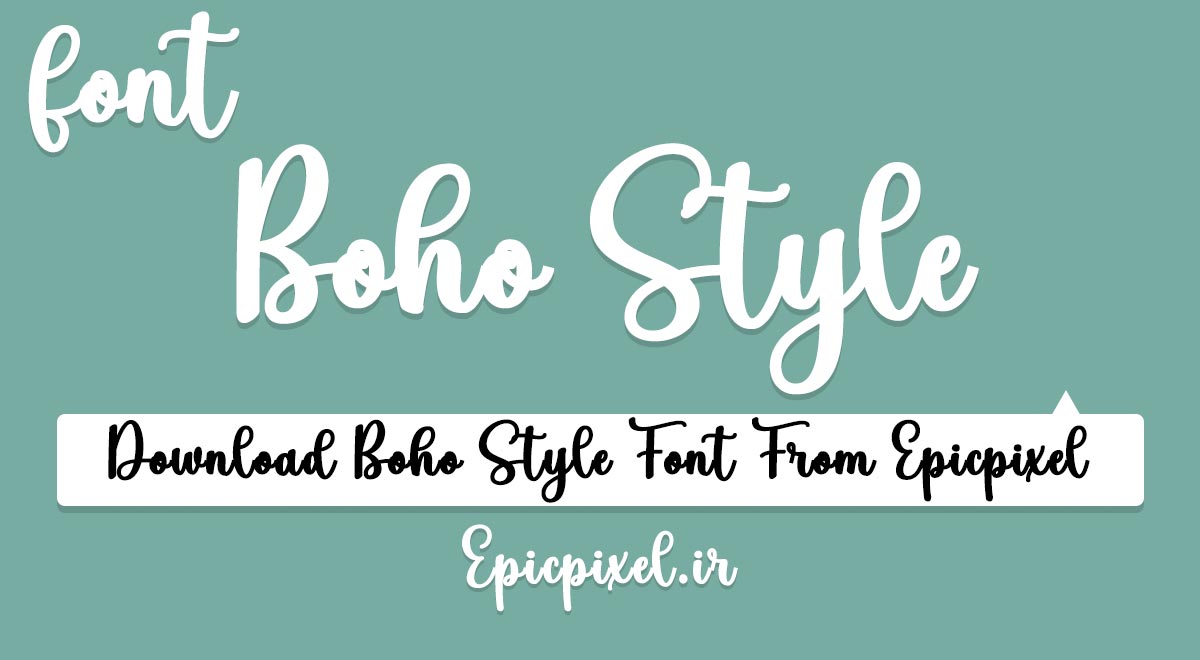
| ⭐ توضیحات | Boho Style Script یک فونت خوشنویسی مدرن از جمله Regular است. این فونت معمولی و زیبا با swashes است. قابل استفاده برای اهداف مختلف. مانند آرم، بسته بندی محصول، دعوت نامه عروسی، نام تجاری، سرفصل ها، علائم، برچسب ها، امضاها، جلد کتاب، پوستر، نقل قول و موارد دیگر.
امکانات: · همه حروف بزرگ و کوچک · جایگزین ها و لیگاتورها · اعداد و نمادها · زبان های پشتیبانی شده · جایگزین ها و کلاسورها PUA های کدگذاری شده |